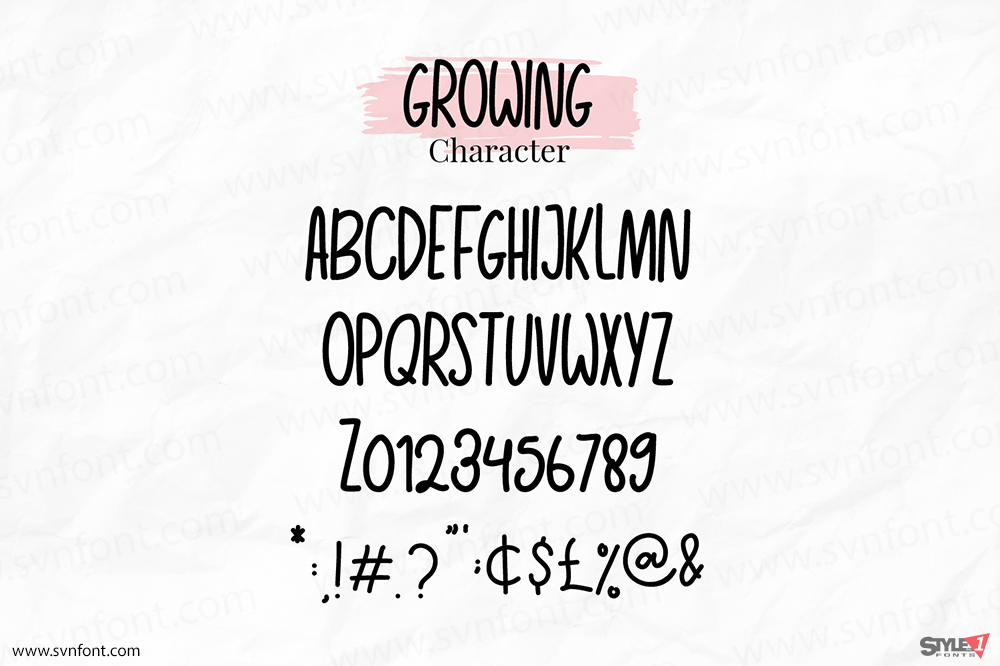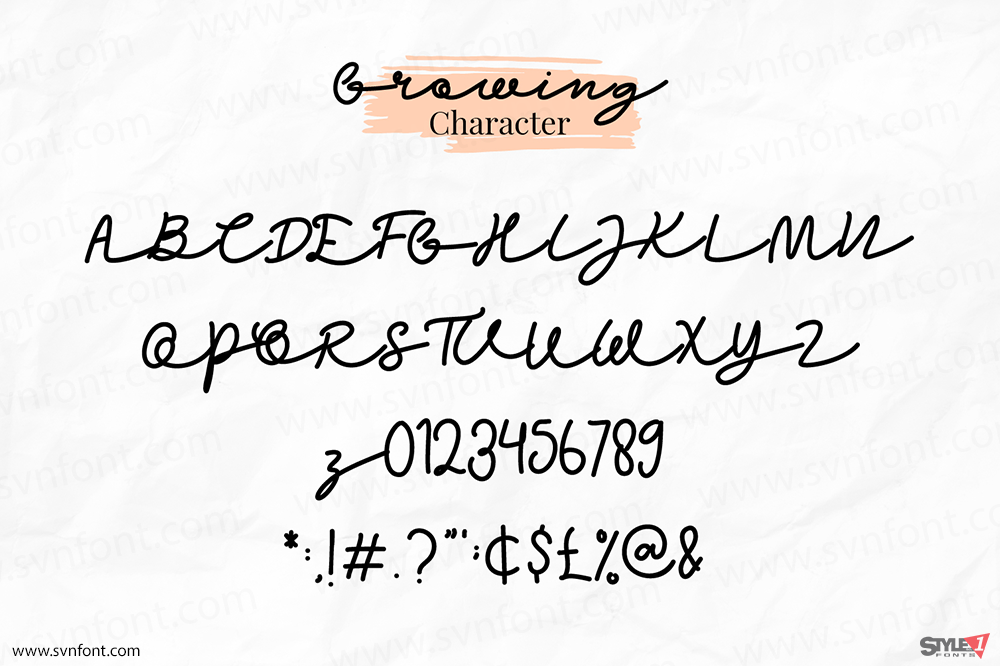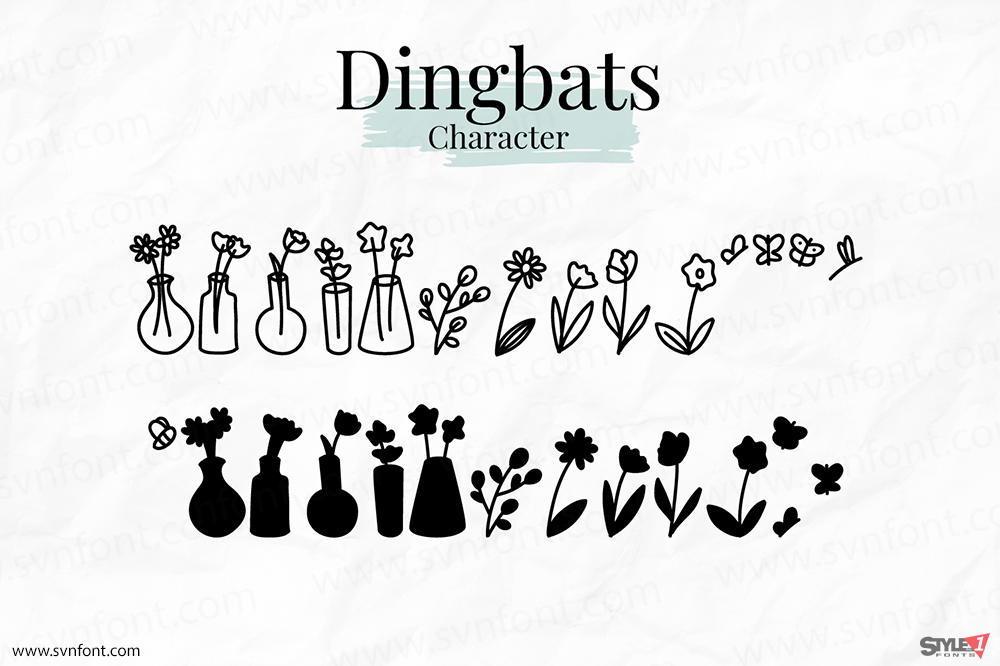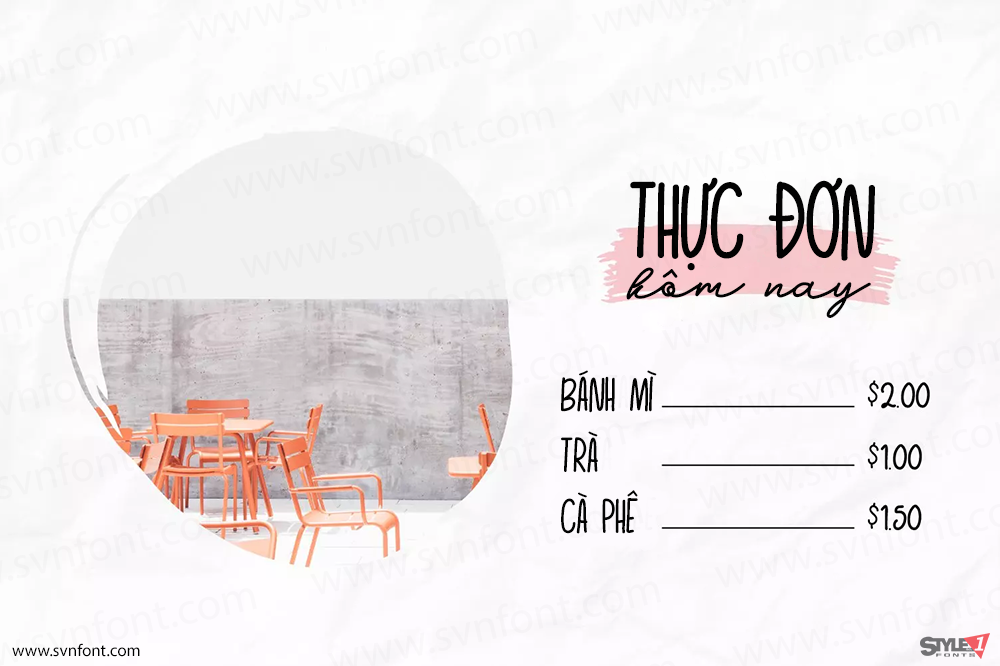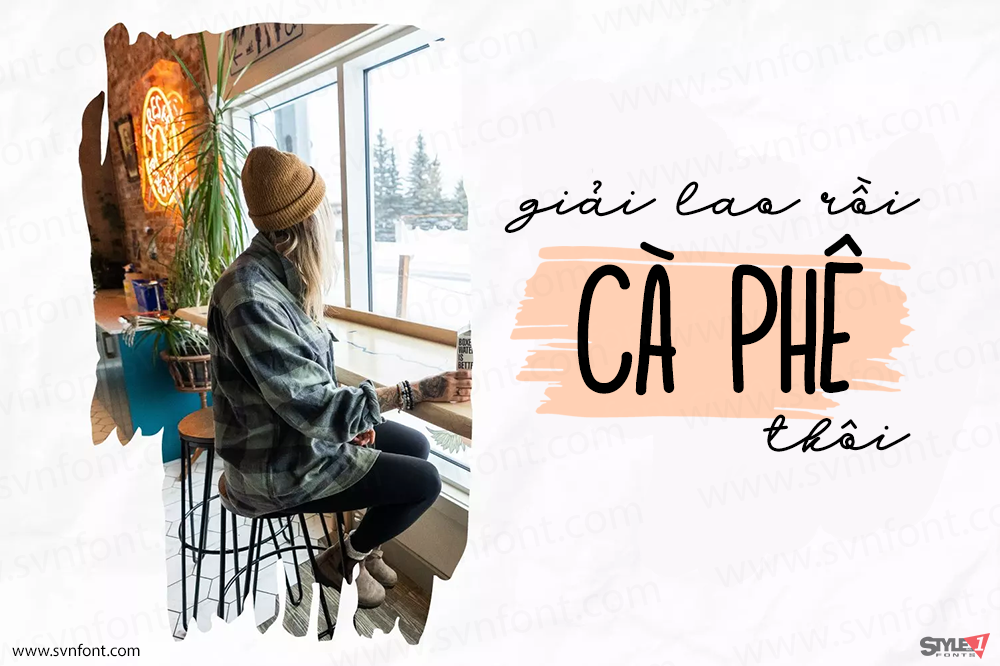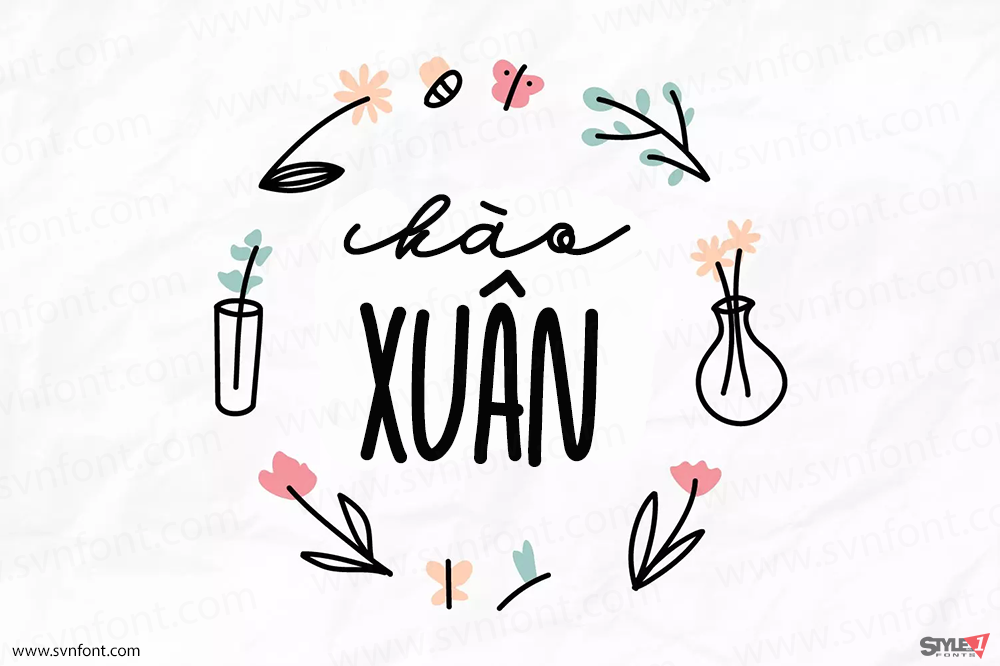
Growing Garden là một bộ ba phông chữ viết tay thanh lịch và tự nhiên. Vẻ ngoài độc đáo này sẽ thu hút nhiều ý tưởng thủ công đa dạng. Nó trông tuyệt đẹp trên thiệp mời đám cưới, thiệp cảm ơn, trích dẫn, thiệp chúc mừng, logo, danh thiếp và mọi thiết kế khác cần một nét chữ viết tay.